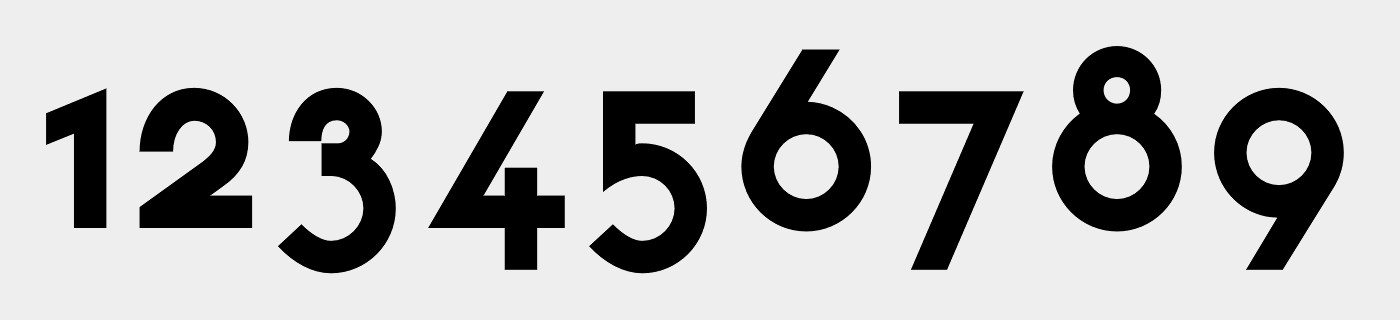
Typische Zifferblatt-Schrift - wie heisst sie?
Weiß jemand wie die Typo der Ziffern auf diesem Zifferblatt heißt oder  wo man sie grob einordnen kann?
Solche Ziffern sieht man häufig auf Wand- und Standuhren aus der frühen Mitte des 20. Jh.
Ist eine geometrische Grotesk. Weiss jetzt nicht genau welche Schrift in deinem Beispiel zu sehen ist, aber die Kabel geht in die Richtung. Und die Bauhaus natürlich auch.
Solche Ziffernsätze entstammen keiner Satzschrift, sondern wurden in der Zeit vor den digitalen Schriften, also bei allem, was länger als etwa 30 Jahre zurück liegt, speziell für den Zweck von einem auf Schrift spezialisierten Grafiker gezeichnet.